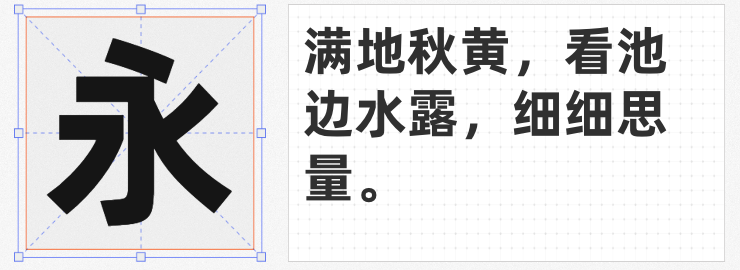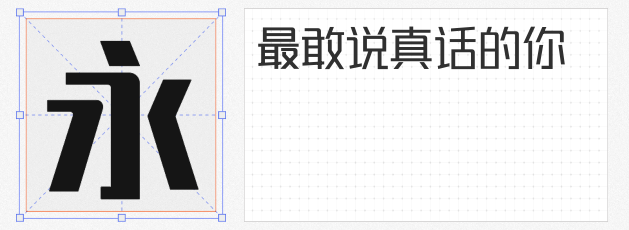
年终大促的战鼓已擂响,如何在视觉设计中抢占先机?一款兼具视觉冲击力与品牌调性的字体,往往能成为破局关键。本文精选四款免费商用字体,从传统书法到现代几何,从力量感到轻盈感,助你打造令人过目难忘的促销设计。
1. 锐字潮牌可变真言2.0简
这款字体以浑厚笔触勾勒出刚柔并济的视觉张力——直角与圆角错落搭配,转折处如刀刻斧凿般利落,收笔处又暗藏婉转弧度。无论是电商主标题的霸气呈现,还是海报中的核心标语,都能通过字体的骨骼感传递出“稳中带锐”的促销气势。其可变特性更支持设计师根据场景调整字重,轻松适配不同媒介的视觉需求。
2. 阿里巴巴普惠体3 95 ExtraBold
专为年轻化品牌打造的普惠体3.0,以95 ExtraBold字重释放出蓬勃能量。瘦长字形与高重心设计,让文字如跃动的数字精灵般充满活力;标题字省略出脚的极简处理,既保留了识别度,又让画面更显通透。尤其适合科技、快消品类的年终促销,用“轻盈感”打破传统促销的厚重印象。
3. USMCC源简特粗体
基于思源宋体反向插值技术生成的这款特粗体,完美继承了思源家族的基因优势。其粗壮字干与纤细衬线的对比,既能作为主标题吸引眼球,又能与常规字重形成层次分明的排版体系。在促销海报中搭配使用,可轻松实现“标题炸场+正文易读”的视觉效果。
4. 一品启航体
这款以传统书法为魂的免费字体,笔锋如刀剑出鞘般昂扬向上,字形结构暗含“破浪前行”的动态感。无论是品牌slogan的升华演绎,还是促销倒计时牌的震撼呈现,都能通过字体的精神内核传递出“锐意进取”的品牌态度。更难得的是其完全开放的商用权限,让设计无后顾之忧。
年终大促的设计战场,字体即是武器。这四款风格迥异却同样强大的免费商用字体,将助你突破创意边界,用文字的力量点燃消费者的购买热情!